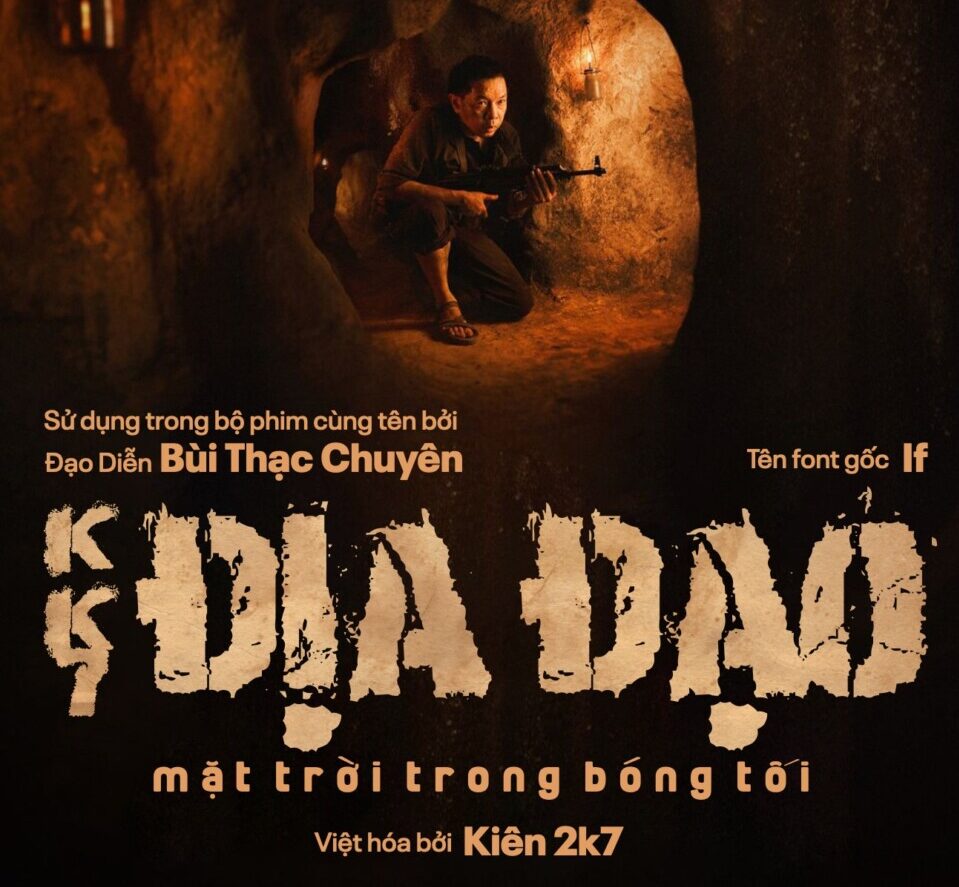
Font Việt hóa phim Địa Đạo – KK7-Địa Đạo
Giới thiệu về Font Việt hóa phim Địa Đạo – KK7-Địa Đạo
Bộ phim điện ảnh Địa Đạo: Mặt Đạo Sinh Tử đã tạo nên một cơn sốt lớn trong làng điện ảnh Việt Nam không chỉ bởi nội dung lịch sử hào hùng mà còn nhờ hệ thống nhận diện hình ảnh cực kỳ ấn tượng. Trong đó, Font Việt hóa phim Địa Đạo – KK7-Địa Đạo đóng vai trò quan trọng trong việc truyền tải tinh thần kiên cường của các chiến sĩ. Đây là bộ Font Miễn Phí được thiết kế với các đường nét mạnh mẽ, góc cạnh nhưng vẫn mang hơi thở hoài cổ, tái hiện chân thực không khí của những năm tháng kháng chiến tại vùng đất thép Củ Chi. Font chữ này hiện được rất nhiều bạn học sinh và giáo viên yêu thích để thiết kế các bài thuyết trình lịch sử sinh động.
Đặc điểm nổi bật của bộ font chữ
Bộ font KK7-Địa Đạo sở hữu phong cách thiết kế độc bản với các nét mô phỏng kiểu chữ in ấn cũ trên báo chí và biểu ngữ thời xưa. Khi sử dụng Font Việt hóa phim Địa Đạo – KK7-Địa Đạo, người dùng sẽ cảm nhận được sự chắc chắn trong từng con chữ, rất phù hợp cho các tiêu đề lớn hoặc poster phim ảnh. Đặc biệt, phiên bản này đã được tối ưu hóa hoàn toàn cho tiếng Việt, giúp tránh lỗi hiển thị các dấu thanh phức tạp.
Cách ứng dụng Font Việt hóa phim Địa Đạo – KK7-Địa Đạo hiệu quả